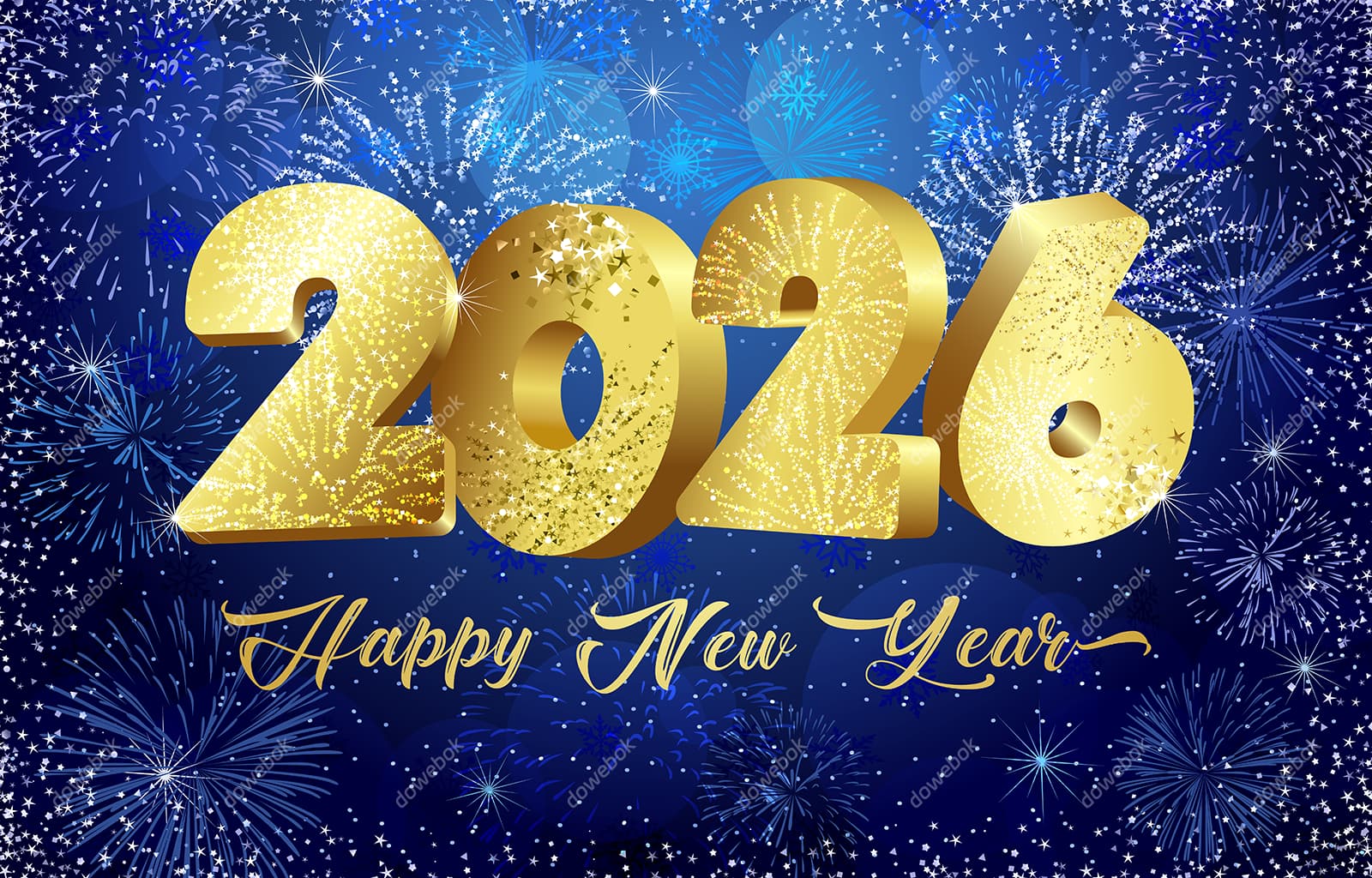
这是一款蓝色背景和金色数字设计 2026 新年快乐矢量素材,深蓝夜空作底,满缀金白烟花与星点,如碎钻铺展,氛围璀璨热烈。立体 “2026” 以鎏金为主色调,字身嵌烟花纹理,光泽华贵亮眼。下方衬着柔美的金色花体 “Happy New Year”,整体用浓郁的蓝金配色与闪耀质感,将跨年的盛大喜庆与精致华丽拉满。